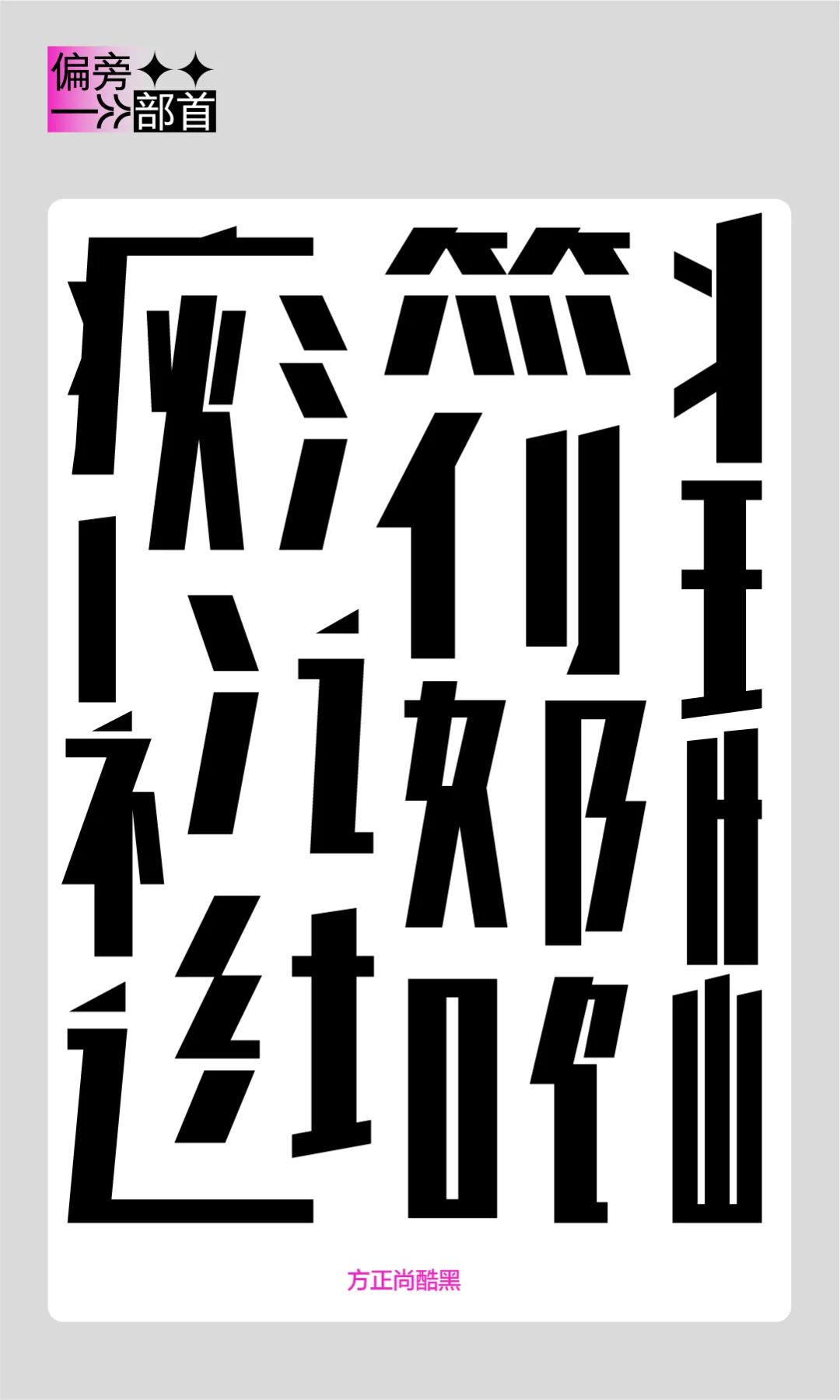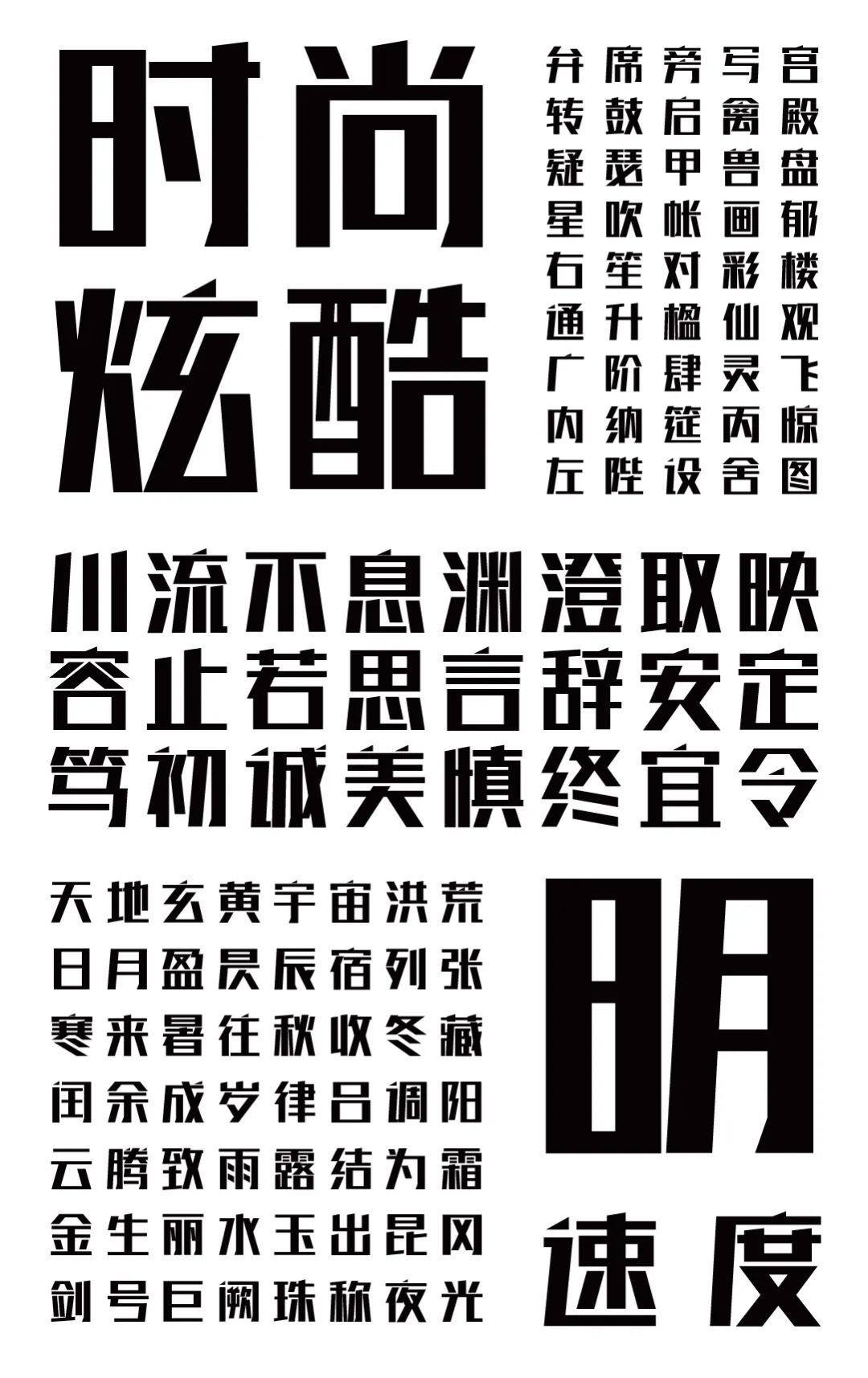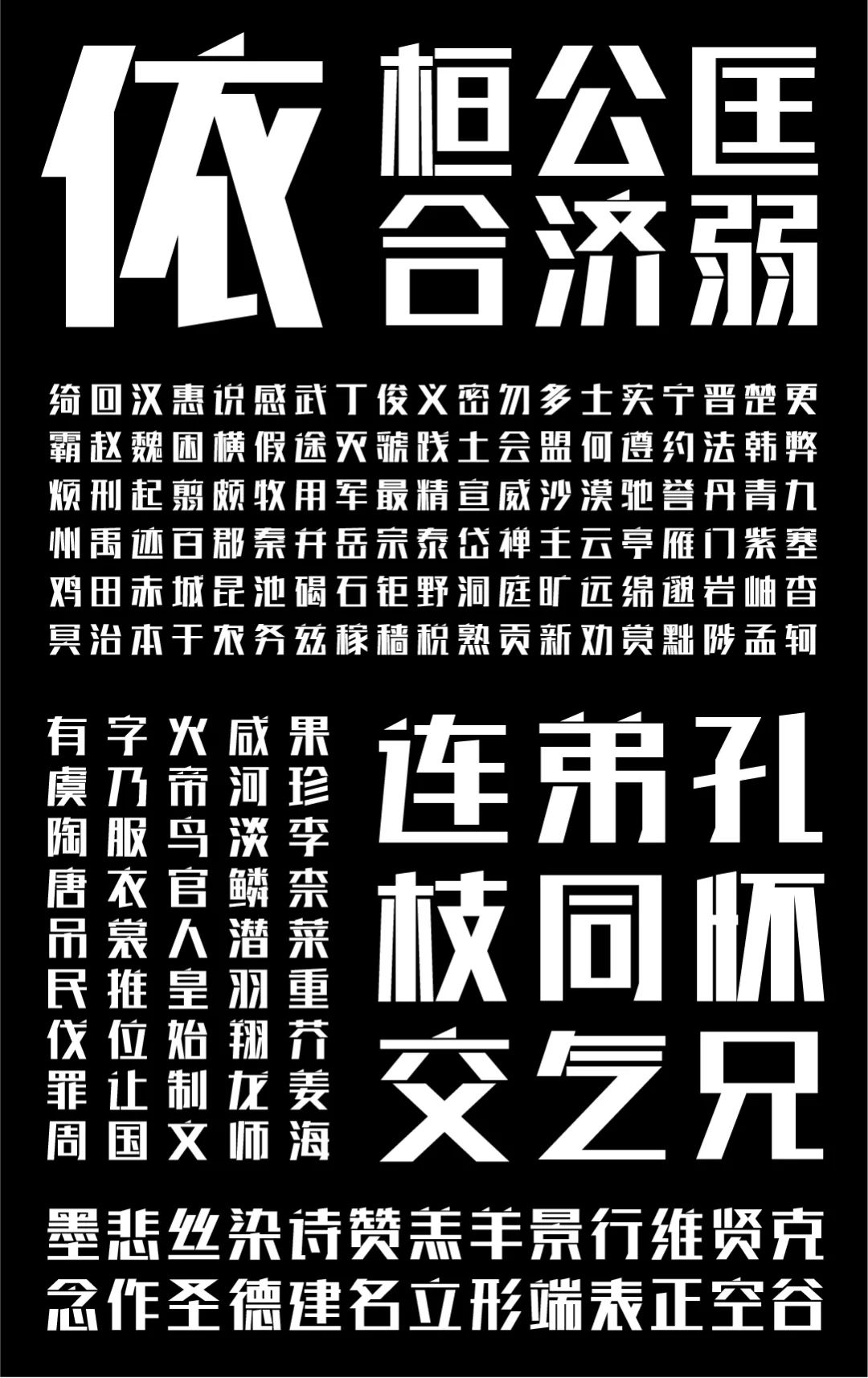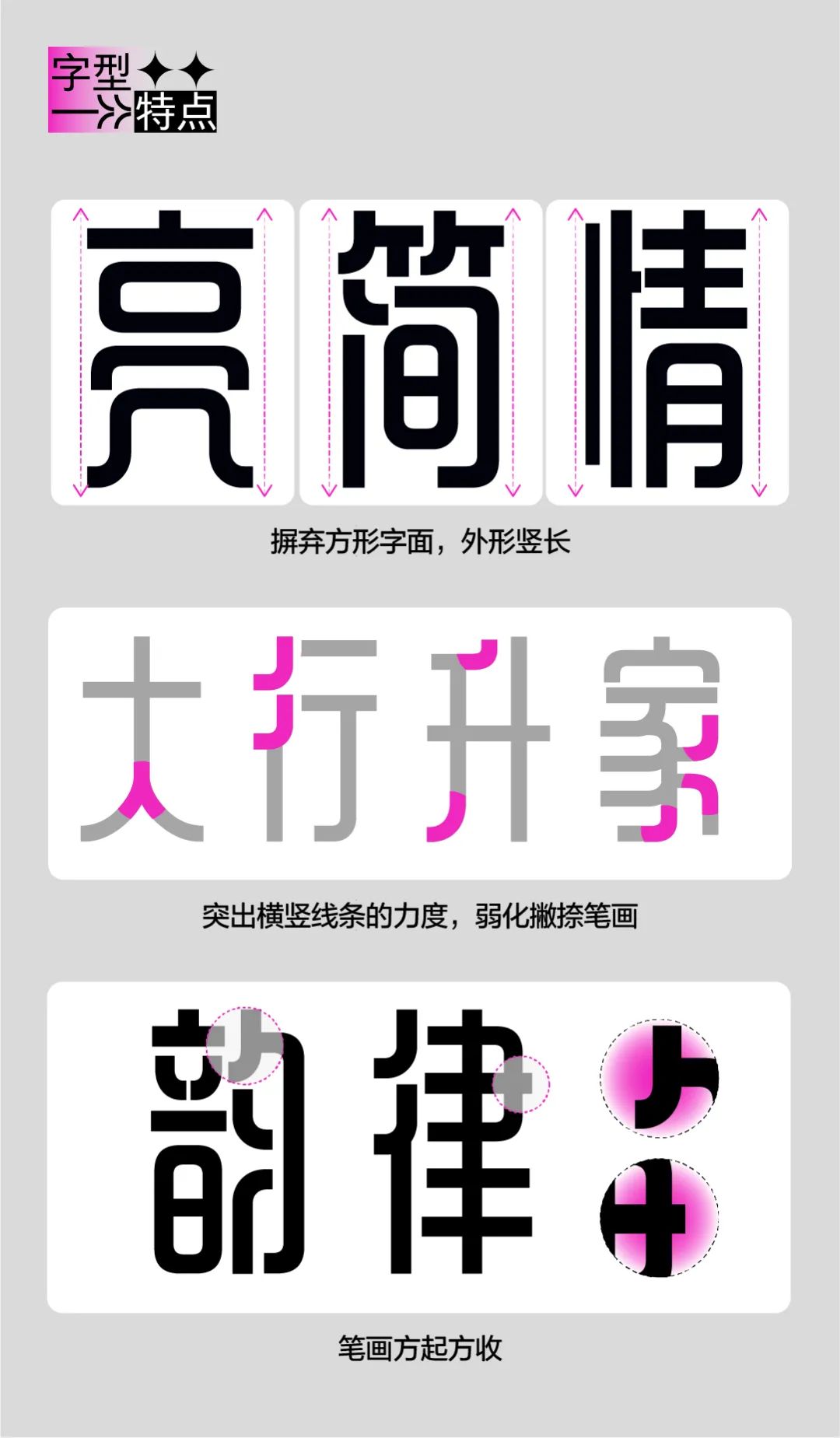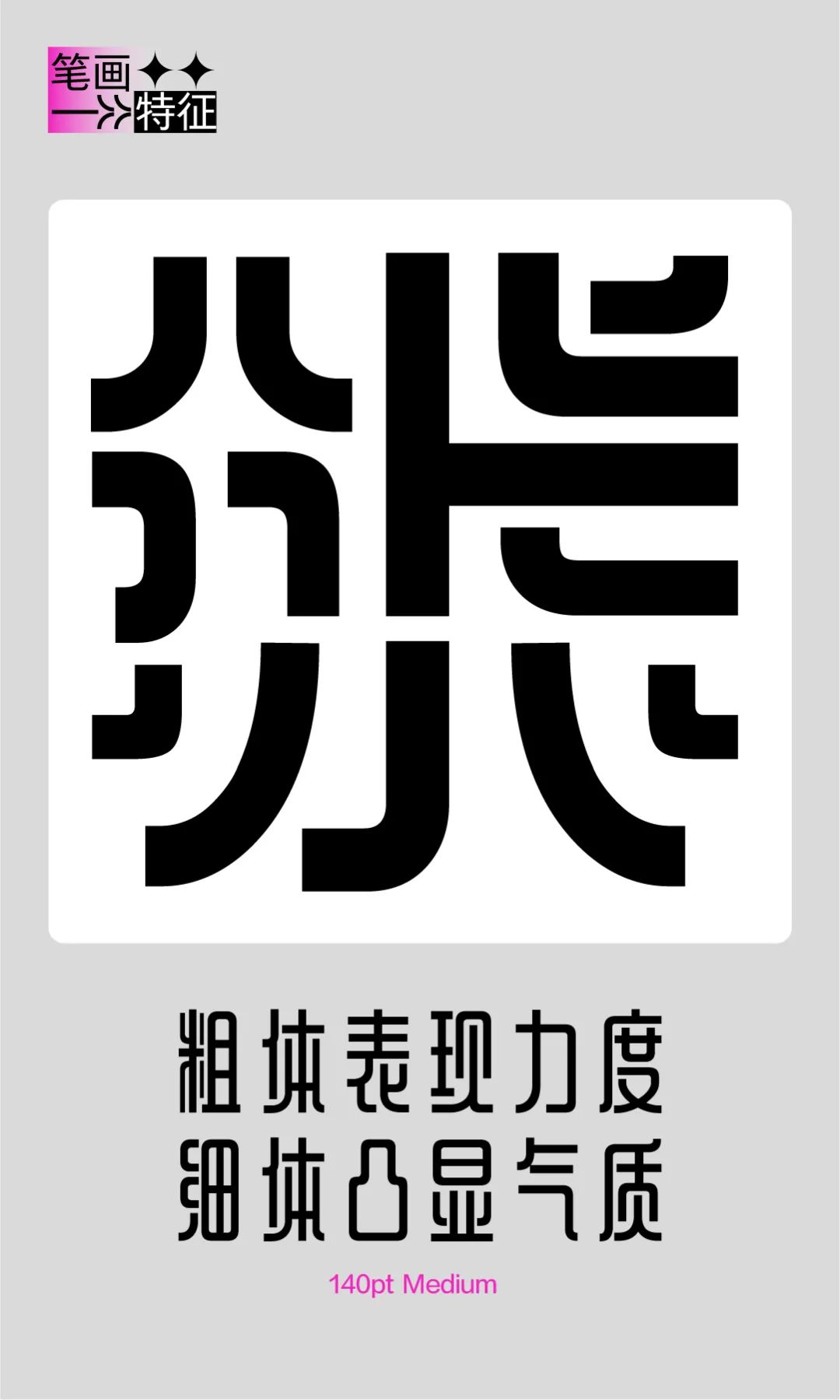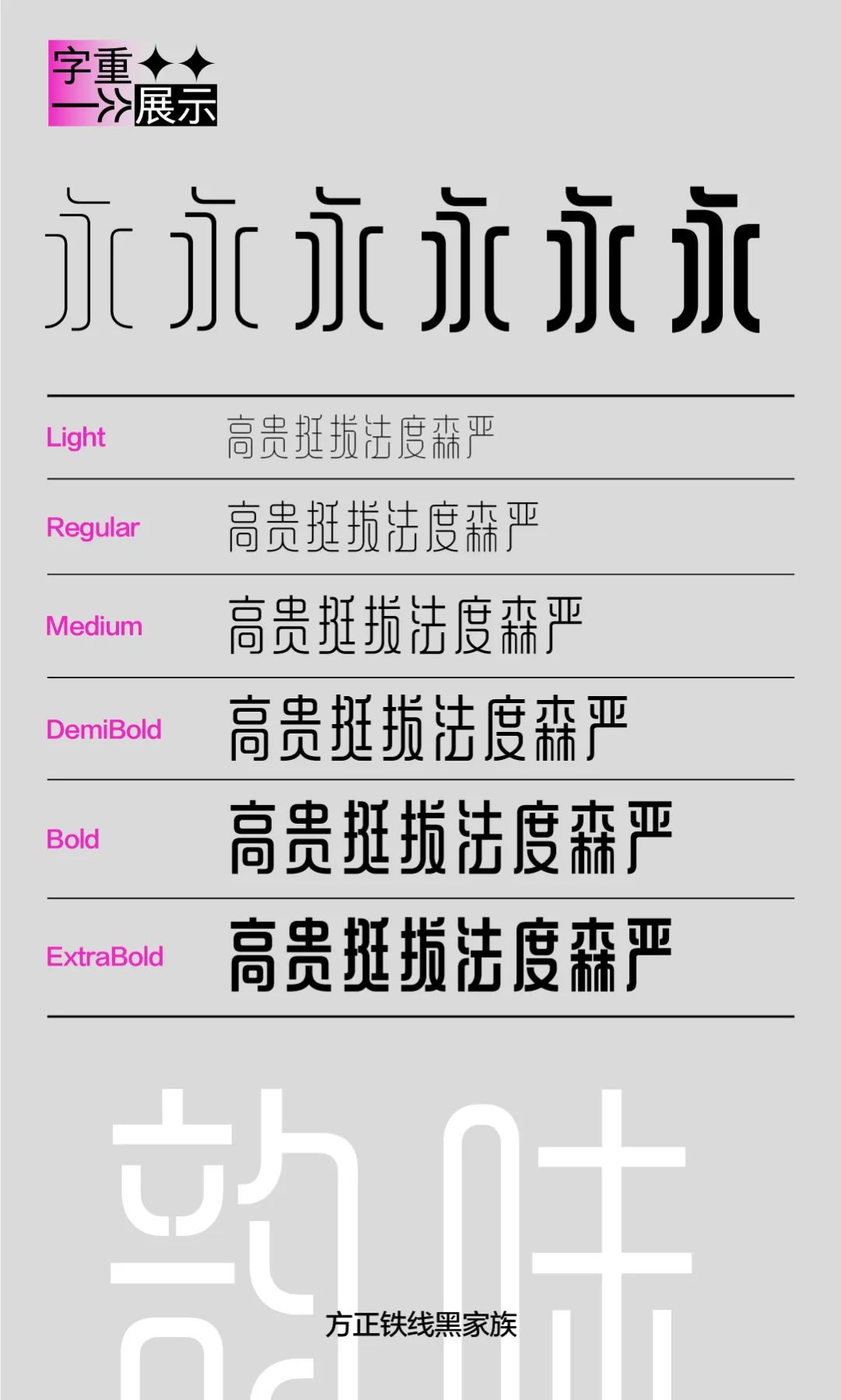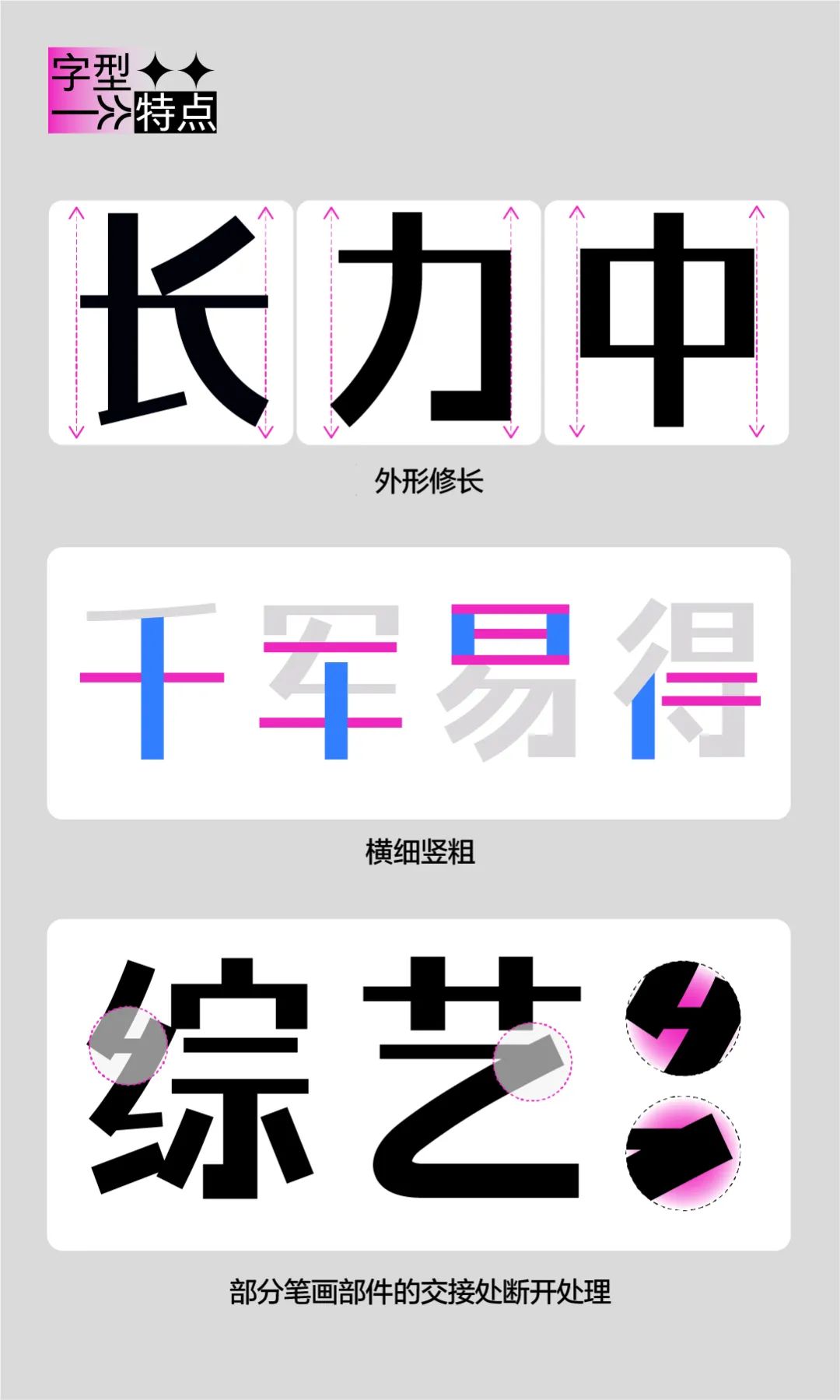
设计师郝君军作客方正字库直播间,为大家分享他的造字心得。
造字如修行——
是什么让我决定成为一名字体设计师?
方正尚酷体打破了传统字体的笔形和结构,将笔画凝练为简练的几何图形,使字型更趋向于图形化处理,抛弃弧线细节,追求用最简洁的设计元素营造丰富而统一的视觉氛围。
大字面、横细竖粗的笔画结构,保证了字面的稳定性;上提的重心,又满足了字面的美观性,达到身短腿长的视觉效果;点与勾的结构处理为三角形,增加了字体的灵动性和犀利感,使字体更有性格与个性。对时尚感与力量感的塑造,恰如这款字体“尚酷”一名。
方正尚酷的个性明快有力,风格时尚酷炫,适用于潮流类品牌的广告、产品包装设计,同时可作为标题字体在海报、书籍、杂志中使用。
方正铁线黑的基因源自于传统书法中的铁线篆书,取法铁线篆书的结构布白,注入现代时尚基因,字形整体竖长,高贵挺拔,摒弃方形字面,更倾向于满足现代横排的应用场景,笔形内方外圆,简约而法度森严,方起方收斩钉截铁,整体既有传统的东方神韵,兼具现代图形设计美感。突出横竖线条的力度,弱化撇捺笔画,强化了印章一般的块面印象,粗体表现力度,细体凸显气质。
方正铁线黑包含6种不同的粗细,多款字重的家族化设计满足不同场景的用字需求,除了适用于时尚、运动、汽车、工业、建筑、艺术、娱乐等领域的广告、包装、品牌、出版物等传统应用环境,更突出多媒体屏显优势,为单调的互联网用字环境提供了新的选择。
方正力黑摒弃了正方形的呆板,字身设置为竖长型,基础部件采用几何造型,犹如用大排刷书写而成,充满力量感;笔画横细竖粗,借鉴少许宋体的特征,在注入优雅基因的同时冲淡粗笔画带来的压迫感;某些笔画部件的连接处做了断笔处理,强调字体的书写性和亲近感。
方正力黑共包含5种不同粗细,粗体力发千钧,细体精细雅致且具备很好的延展可能,适用于时尚、工业、艺术等多领域的广告、包装、品牌、出版物设计。
所谓“从心所欲不逾矩”,在探索一整套字库的设计方法之余,郝君军坚持将字体创作作为洞察世界重要手段之一,让字体生活化,成为一种习惯,成为一种常态。
▶ 字体日记选作
▶ 节气海报选作
▶ 品牌LOGO选作
▶ 创意设计选作
▶ 书法练习选作